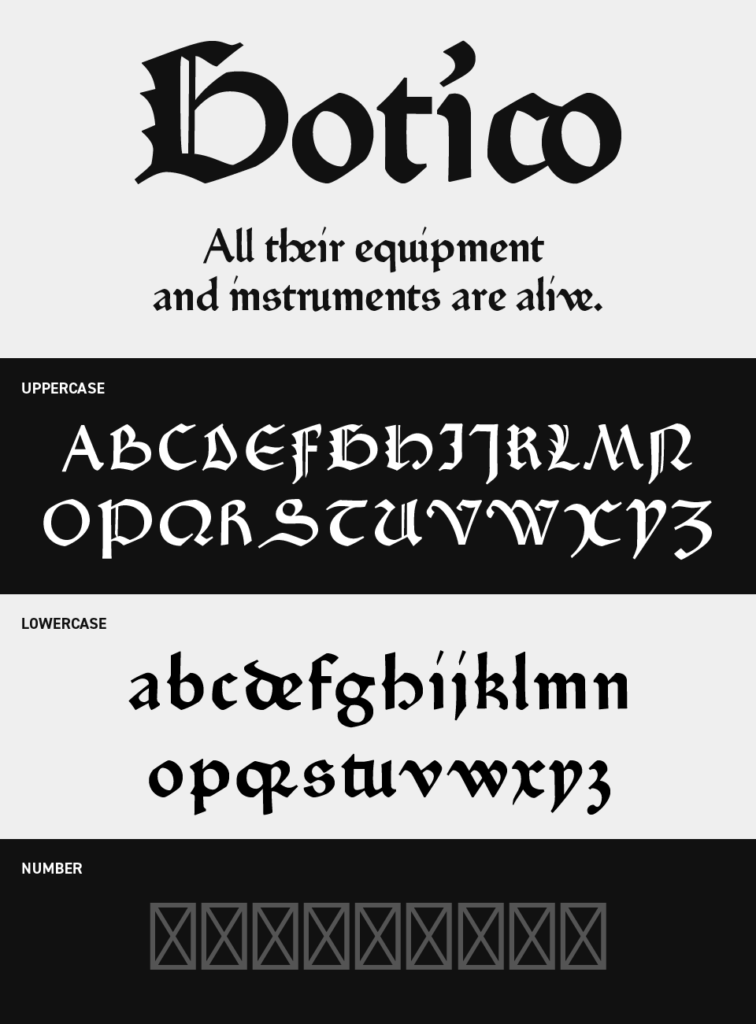
Goticoフォントは、重厚なブラックレターをベースにしたクラシカルな存在感が光るフォントです。
鋭いエッジとユニークな曲線が組み合わさり、中世的な雰囲気と威厳を感じさせる字形が特徴的なフォントです。装飾性が高く、ひと文字ごとに強い個性が感じられる見ていても楽しめるデザインのフォントです。
ファンタジーなどはもちろんですが、ロックやメタル系のビジュアル、歴史や魔法などをテーマにしたデザインにもぴったりなフォントです。